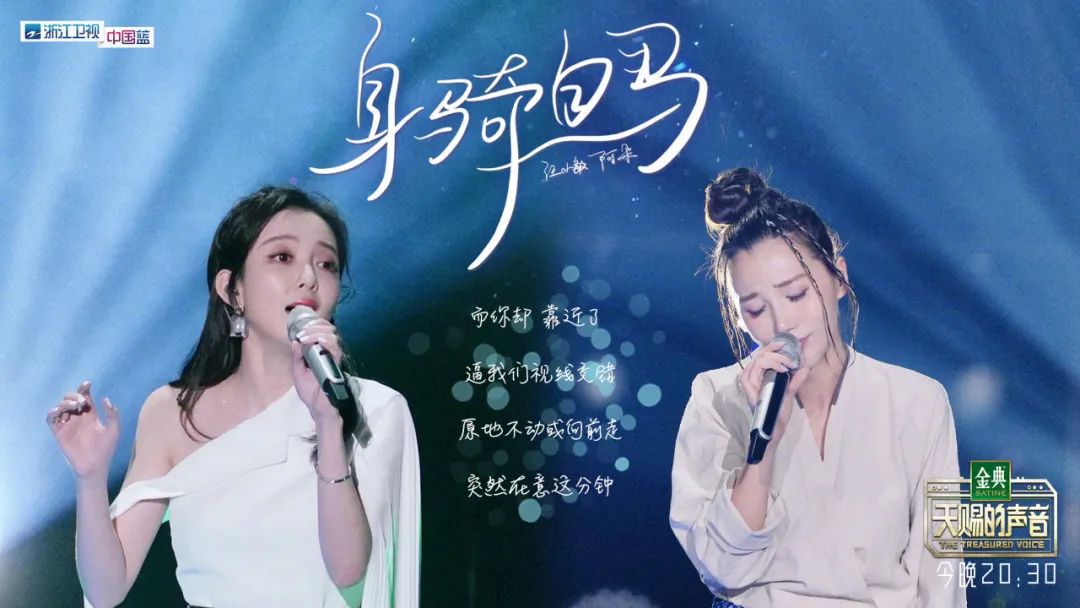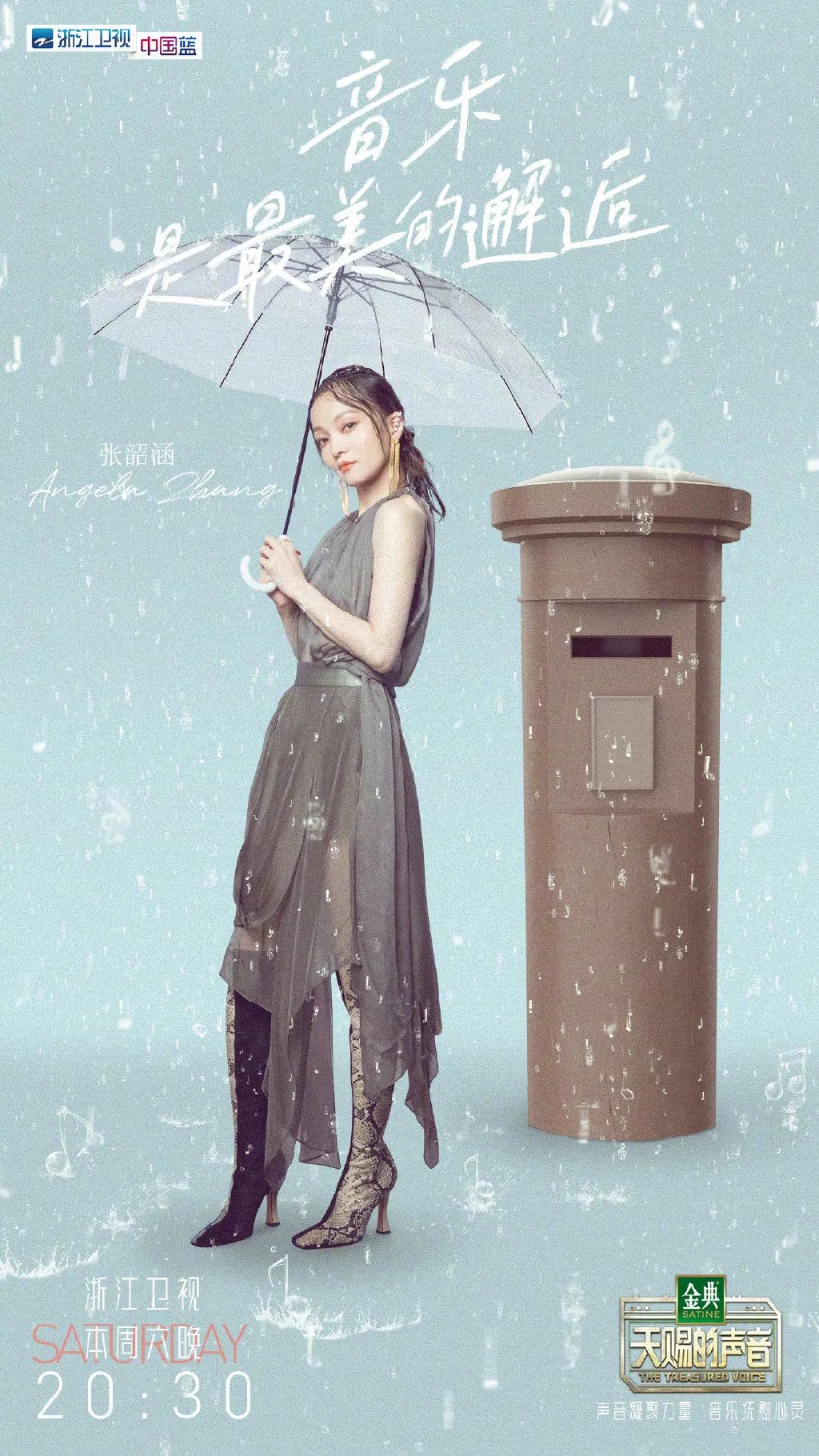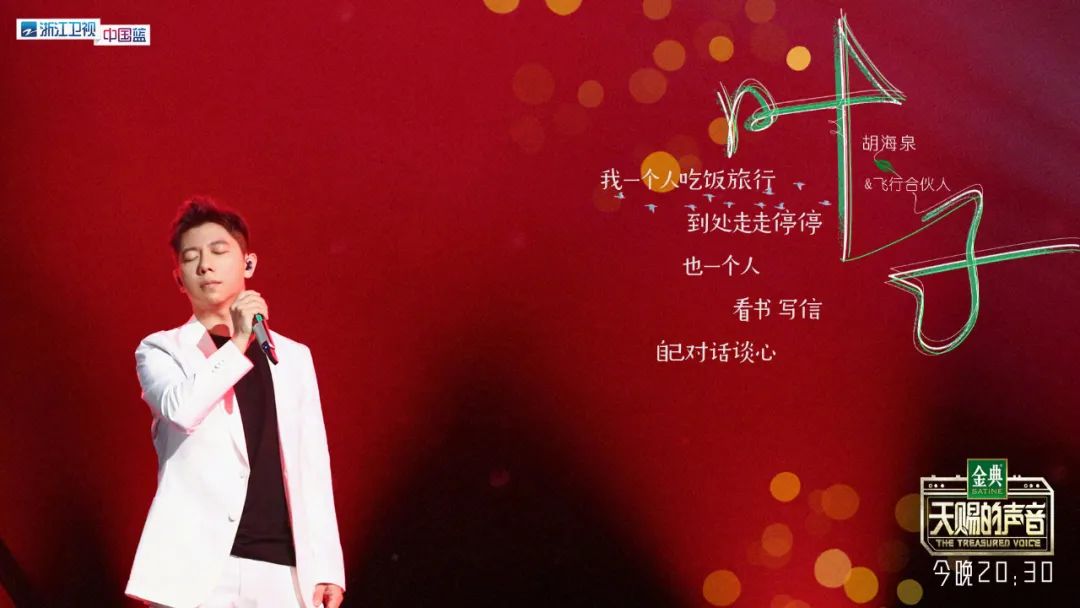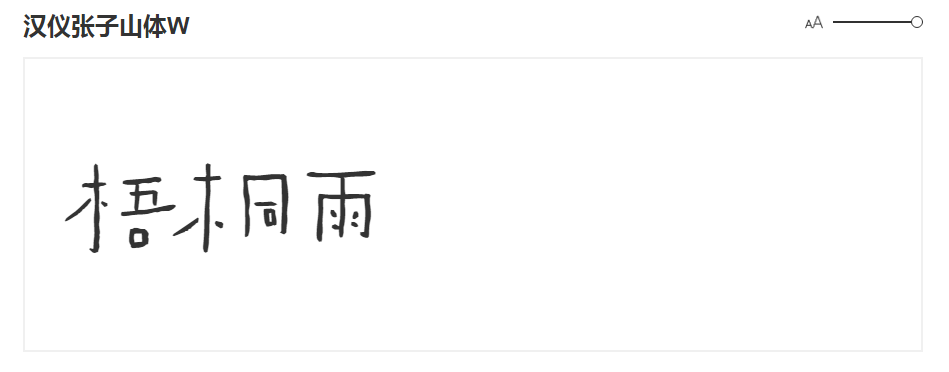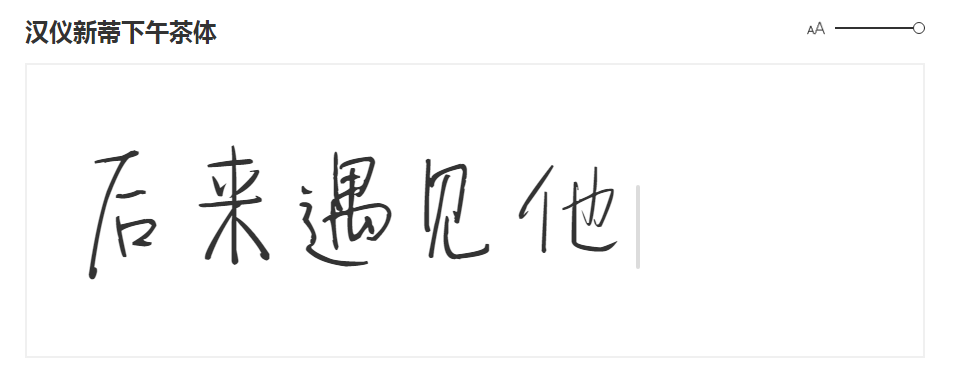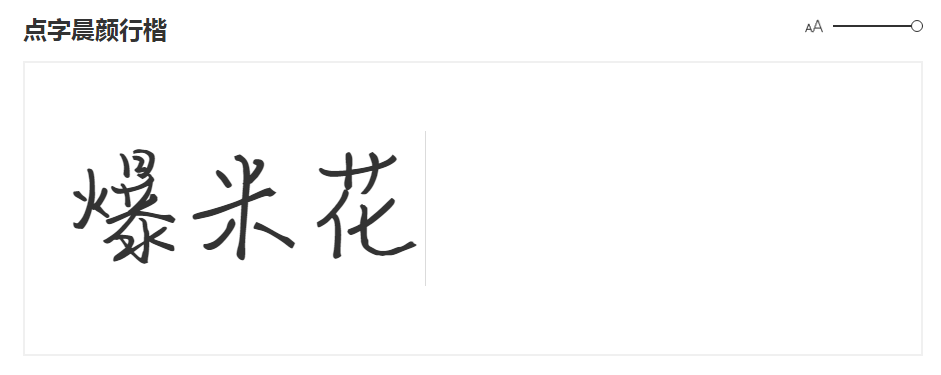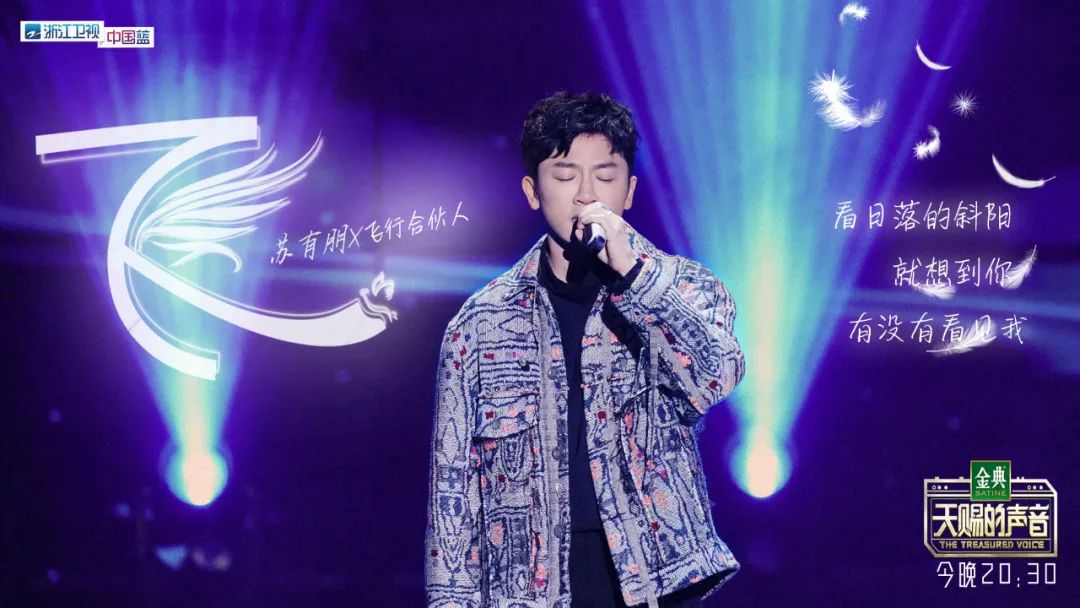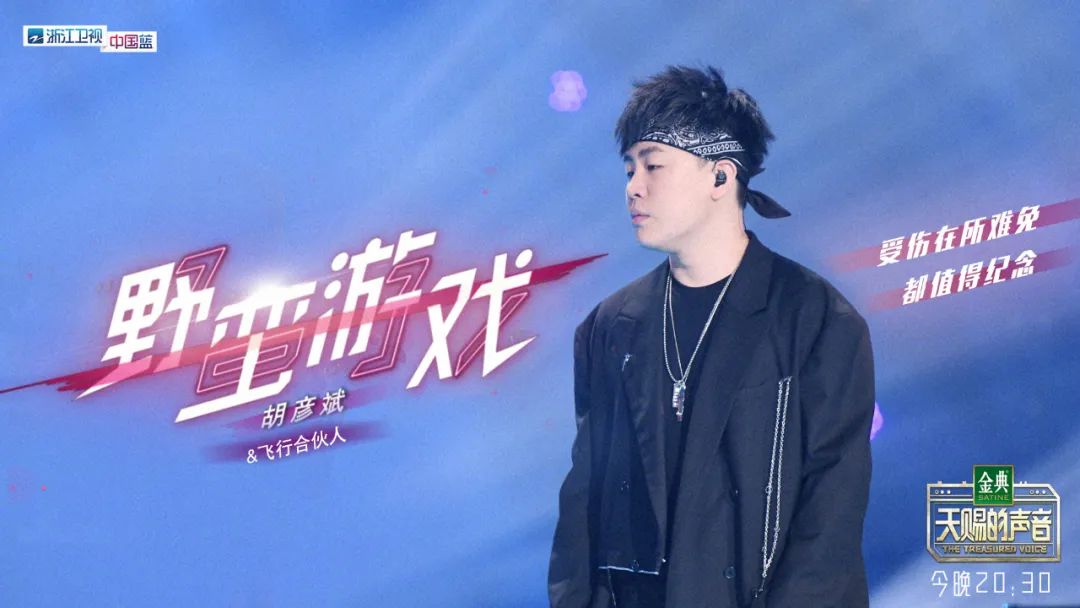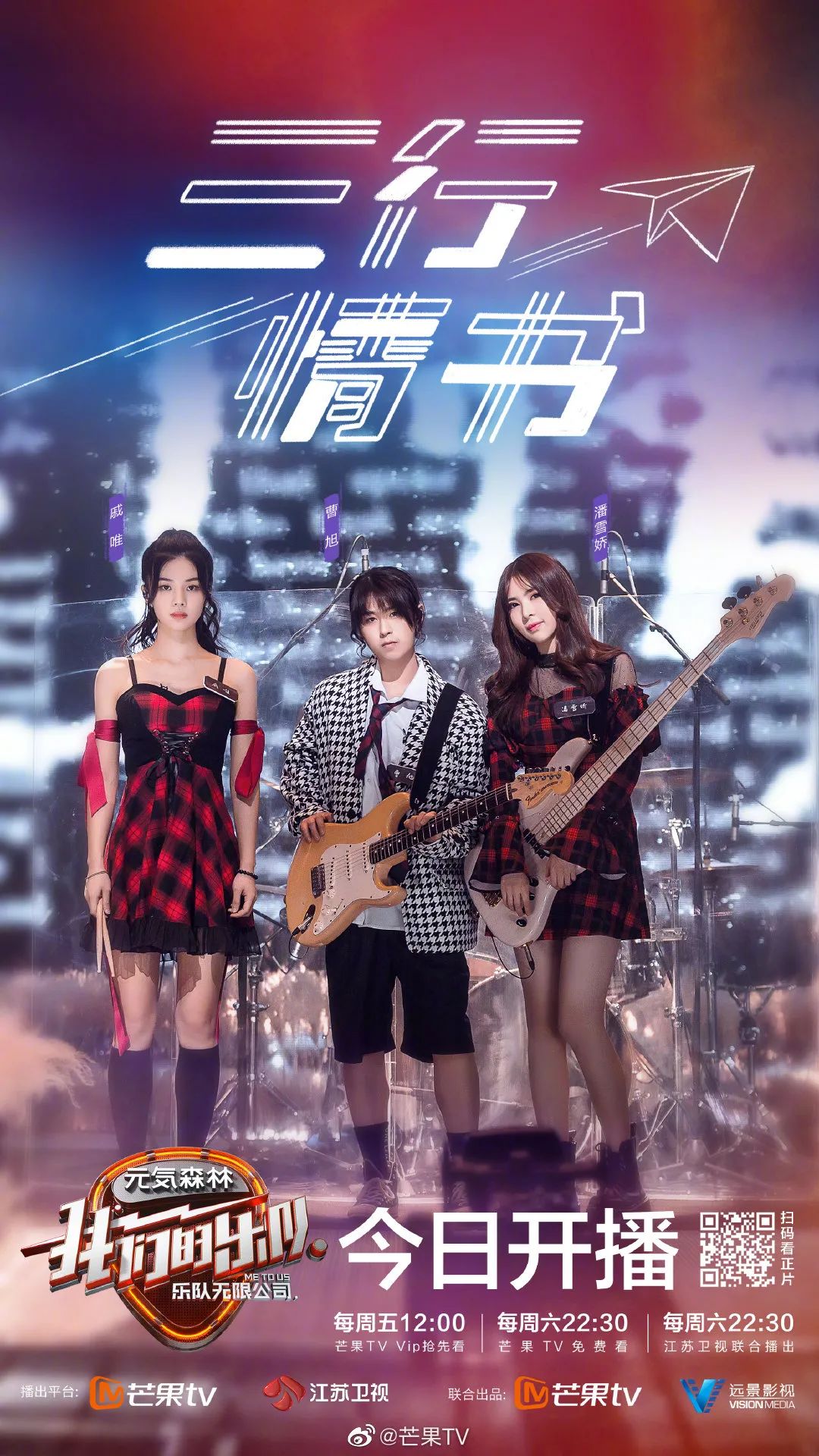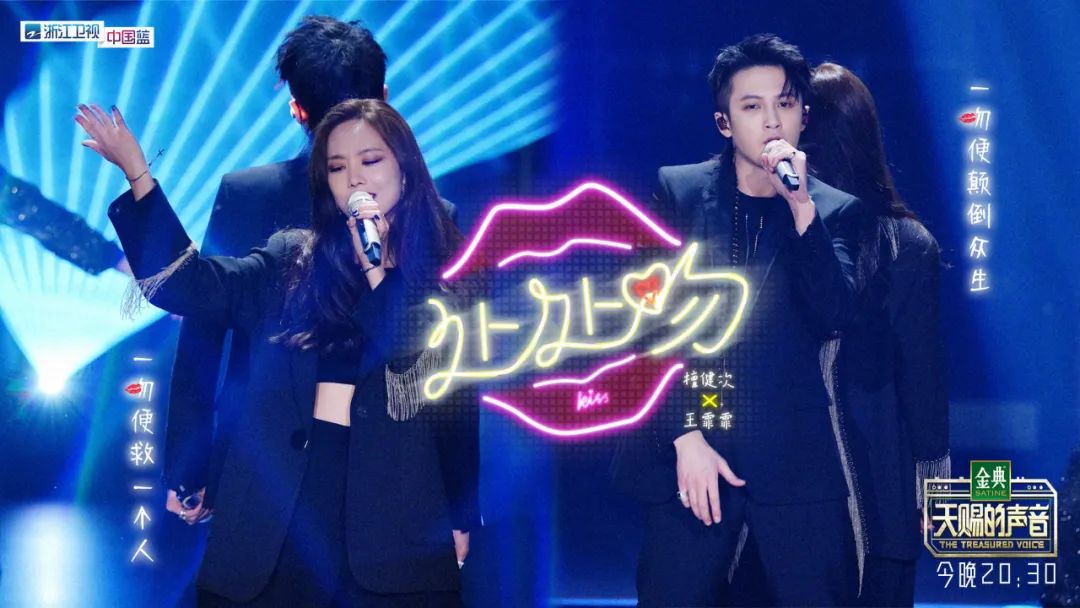
想让字体更撩人,不妨从歌名设计开始
最近是不是憋坏了,想用音乐发泄发泄?别着急,k歌还要再耐心等等,不过看别人k歌也不错。
尤其是那些养眼的歌名设计,让人能一眼跟着文字动情,听着旋律想象,今天我们就一起来康康~
手写的温度
手写的本来就有温度,所以应用在抒情歌名上,最是润物细无声。
字由上有很多手写字,每一款都有独特的气质~
重塑笔画
在字体的基础上,进行笔画的删减替换,最是讨巧,有一种旧貌换新颜的感觉。
所以你需要一些好看的百搭字,变换造型。
华丽装饰
还有一种把歌名做成像logo、招牌一样,在字体的基础上,营造氛围。
这种就看你想要什么风格,就选择什么字体~
最后柚子想说,曾几何时,我们攒着几个月的零花钱,买着心爱的音乐专辑,珍藏到现在都舍不得扔,那是一种情感的寄托,也是一种设计的吸引,现在它以另一种形式出现,我知道,那不仅仅是歌名,而是一首字体和旋律的交响曲。